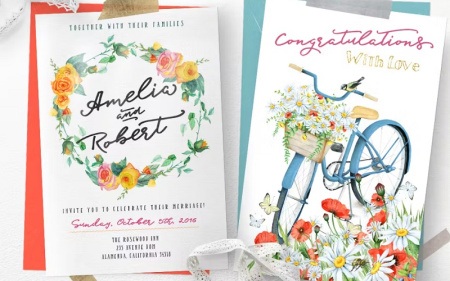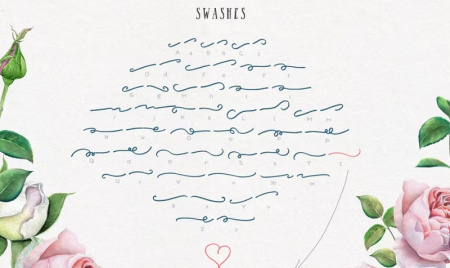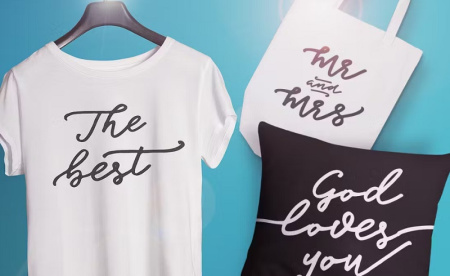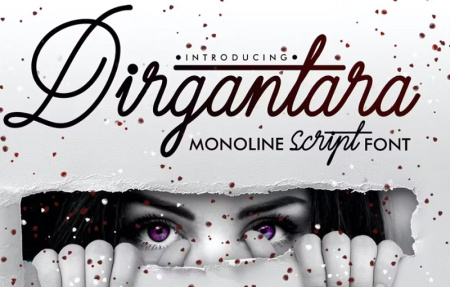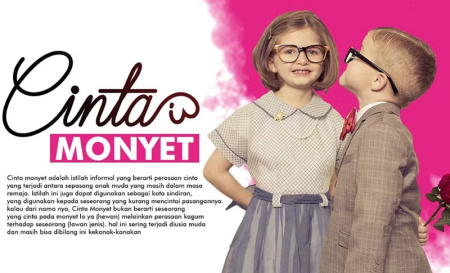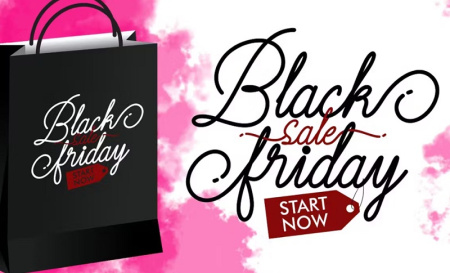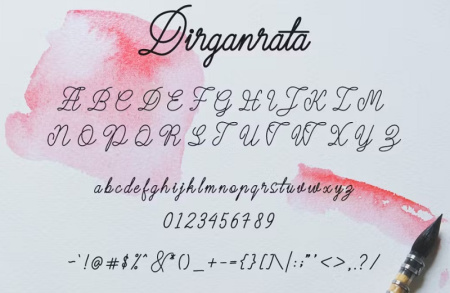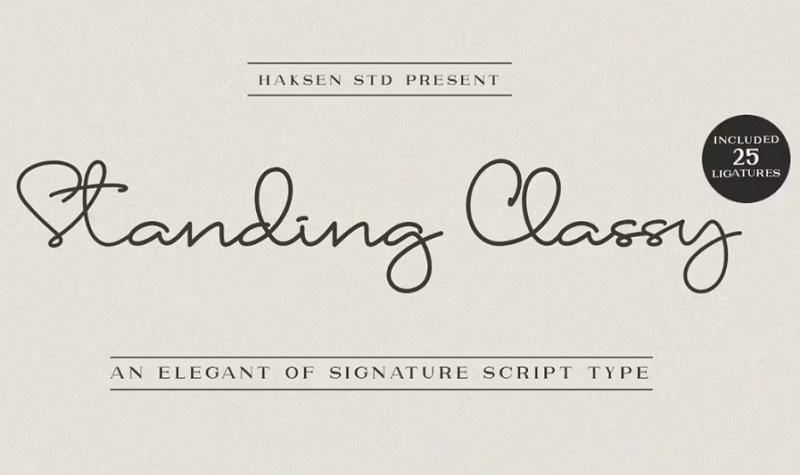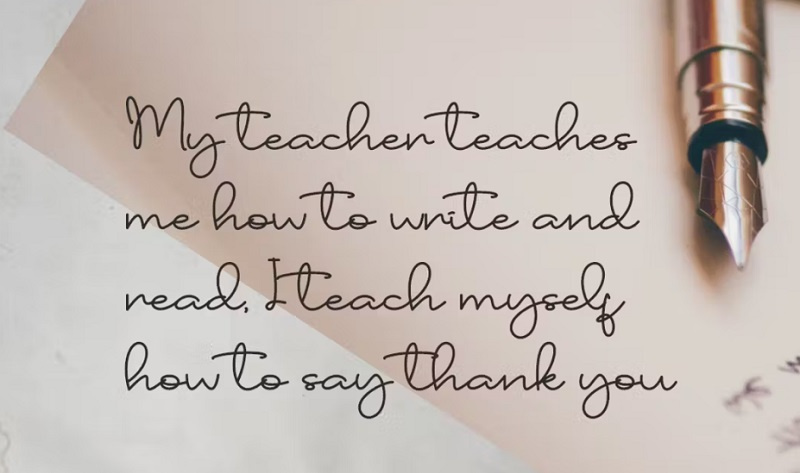
فونت انگلیسی پیوسته شامل 3 فونت انگلیسی سرهم می باشد. این فونت ها بسیار زیبا در طراحی هایی از جمله کارت پستال، نام تجاری، کارت ویزیت، نقل قول، پوستر، آرم و لوگو می باشد. با دانلود فونت انگلیسی پیوسته بهترین فونت ها را برای طراحی و ادیت عکس خواهید داشت. این فونت ها بسیار ظریف و شیک است و مناسب هر نوع طراحی می باشد. برای مشاهده تصاویر این مجموعه در ادامه مطلب با ما همراه باشید.
1- دانلود فونت انگلیسی پیوسته Blessed Script
این فونت انگلیسی پیوسته یک فونت زیبا با طراحی دست نوشته و ظریف است که ظاهری کاملاً منحصر به فرد برای هر کلمه به شما می دهد. این فونت انگلیسی به هم پیوسته از نویسههای چند زبانه پشتیبانی میکنند. فونت برای بسیاری از پروژه های مختلف مانند نقل قول، لوگو، سربرگ وبلاگ، پوستر و ... مناسب است.
2- فونت خط پیوسته انگلیسی Dirgantara
فونت خط پیوسته انگلیسی Dirgantara بسیار زیبا در طراحی کارت پستال، مواد نام تجاری، کارت ویزیت، نقل قول، پوستر و غیره است. این فونت انگلیسی بهم پیوسته قابلیت پشتیبانی چند زبانه را دارد و شامل OTF/TTF/WOFF می باشد.